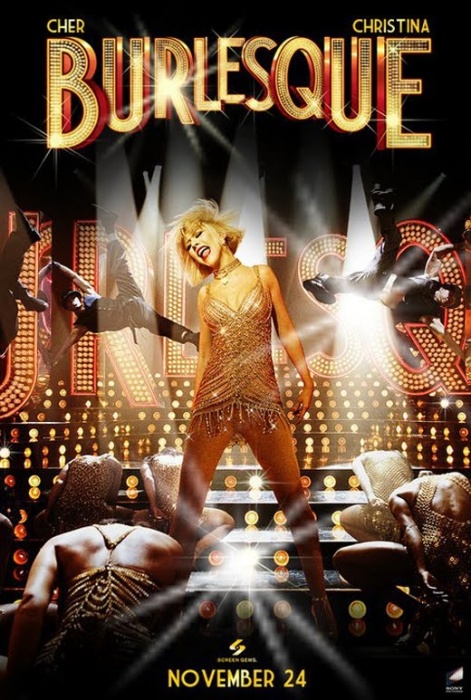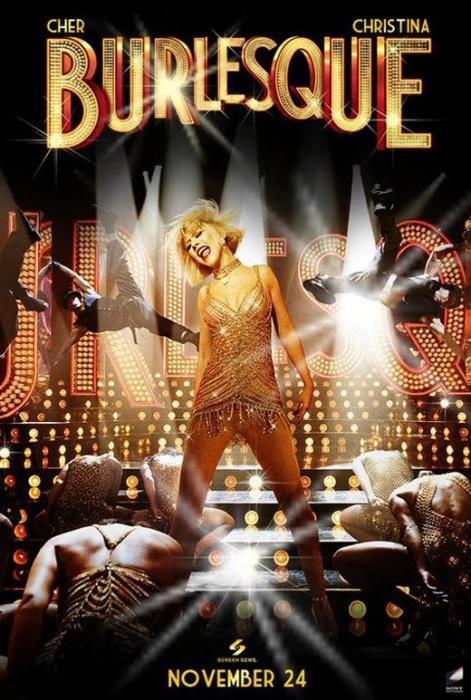
Welche Schrift könnte das sein?
Suche für einen Flyer den Namen dieser Schrift. Kann mir jemand helfen?
Die haben wir gefühlt schon tausend Mal gesucht … "Art Deco", "Art nouveau" und "30er Jahre" könnten dir bei der Suche weiterhelfen. Mir fällt’s nicht ein.